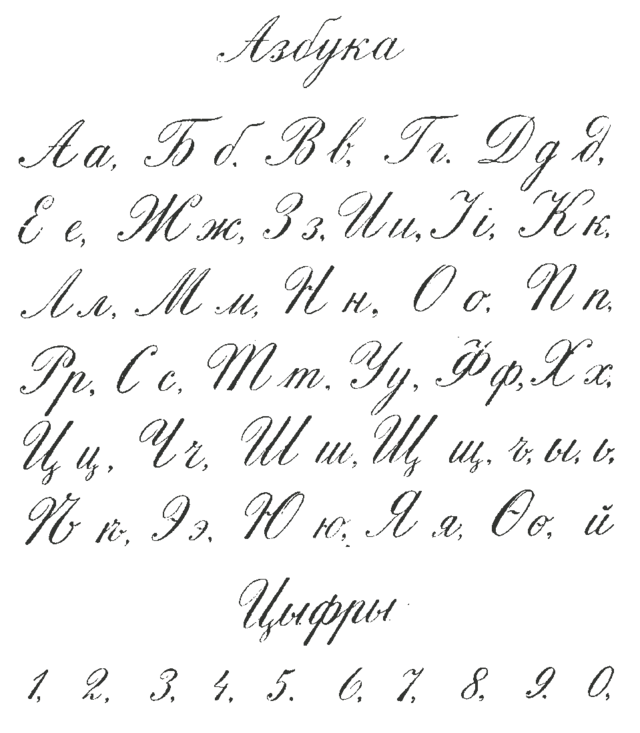
Рукописные шрифты особенности и происхождение гарнитур
Рукописные шрифты принято делить на следующие подгруппы:
- Формальные
- Неформальные
- Каллиграфические.
Первый известный рукописный шрифт, или скоропись (во Франции называемая lettre courante (беглый почерк), а в Англии — secretary hand (почерк секретаря), возник как формальное письмо и был нарезан Робером Гранжоном в середине XVI века, но самые первые основанные на рукописном письме гарнитуры, называемые канчелляреска, создали в Италии еще в конце XV века. Из гарнитур канчеллярески ХХ века стоит упомянуть Zapf Chancery (Герман Цапф, 1979) и Poetica (Роберт Слимбах, 1992) — расширенную гарнитуру с большим набором альтернативных символов, орнаментов и росчерков.
Формальные рукописные шрифты произошли от письма XVII века, у большинства из них наклонные, округлые буквы с соединительными штрихами. К этой категории относится много гарнитур, от строго формальной Snell Roundhand (Мэтью Картер, 1966) до универсальной Ashley Script (Эшли Хэвинден, 1955).
Неформальные шрифты ближе к естественному рукописному письму ручкой или кистью. Обычно в них присутствуют соединительные штрихи. Гарнитуры этой категории очень варьируются по внешнему виду: от непринужденной Brush Script (Роберт И. Смит, 1942) до размашистой Pronto (Алехандро Пауль, 2009).
Каллиграфические гарнитуры произошли от каллиграфического письма, буквы у них не всегда соединены и обычно выглядят как написанные плоским пером. Внешне гарнитуры очень отличаются друг от друга, как, например, сдержанная Vivaldi (Фриц Петерс, 1990) и экспрессивная Riptide (Тимоти Дональдсон, 1996).
Характеристики
У всех рукописных шрифтов есть один общий признак: они кажутся написанными от руки, а не отлитыми, высеченными или изображенными механическим способом.
Помимо этого, они варьируются по стилю и характеристикам и бывают формальными и неформальными, вертикальными и наклонными; у них высокий контраст ширины штрихов, а буквы угловатые, с длинными верхними и нижними выносными элементами; они соединяются друг с другом штрихом или стоят по отдельности.
Применение
В основном рукописные шрифты выполняют декоративные функции, поскольку почти ни один из них не подходит для набора текстовым кеглем или сплошным текстом. Чаще всего они используются для заголовков или акциденций.
Образцы рукописных шрифтов:
- Bickham Script (Ричард Липтон, 1997)
- Byron (Пэт Хиксон, 1992)
- Cascade (Мэтью Картер, 1966)
- Choc (Роджер Экскоффон, 1955)
- Citadel (Monotype Design Studio, 2003)
- Coronet (Роберт Хантер Миддлтон, 1937)
- lsadora (Крис Холме, 1985)
- Monoline Script (Monotype Design Studio, 1933)
- Riptide (Тимоти Дональдсон, 1996)
- Snell Roundhand (Мэтью Картер, 1966)
- Vivaldi (Фриц Петерс, 1970)
- Zapf Chancery (Герман Цапф, 1979)
Шрифты для проектов, планов и карт 12
В эту группу включены: шрифт Каллиграфический, шрифт Пром-
стройпроект и Древний (наклонный).
Каллиграфическое письмо (прил. 37 и 38) относится к скорописным
шрифтам и может с успехом выполняться ученическими перьями, авто¬
ручкой с ’’мягким” пером или шариковой ручкой. Шрифт может найти
применение при оформлении титула, авантитула и шмуцтитула сельско¬
хозяйственных атласов, а также для оформления других вспомогатель¬
ных графических материалов.
Шрифт выполняется с наклоном вправо под углом примерно 60 • По
быстроте исполнения он экономичен, в написании красив и хорошо чи¬
тается.
Прописные и строчные буквы шрифта просты и состоят из двух ос¬
новных элементов: основного (контрастного) и соединительного (пря¬
мого или овального). В основу построения большинства строчных букв
положен овал. Прописные буквы имеют более сложный рисунок.
При выполнении письма ученическим пером или авторучкой шрифт
приобретает ярко выраженный контрастный характер, но при этом сле¬
дует соблюдать чередование тонких и нажимных элементов, которые в
местах закругления круто, изящно и плавно переходят к соединитель¬
ному тонкому штриху.
Строчные нормальные буквы имеют плотность примерно 1:2, а широ¬
кие ж, м, т, ф, ш, щ, ы, ю — 1:1.
Буквы б, в, д, р, у, ф, ц, щ имеют выносные подстрочные и надстроч¬
ные элементы.
Прописные буквы разделяются на узкие (при плотности 2:4) —А, Е, 3,
О, С, Ь, Э, нормальные (4:4) -Н, П, Р, X, Ц и широкие (5:4) -Ж, М, Т, Ш,
Щ, Ы. Поперечные элементы прописных букв 3, К, Е, Н, Ю пишут не¬
сколько выше геометрической середины буквы.
Толщина основного элемента всех букв одинакова и составляет вели¬
чину (1/7) Н.
Буквы в словах пишутся слитно, причем для большей выразительнос¬
Концевые элементы у прописных и строчных букв могут быть петле¬
образными, пламевидными, овально-спиральными и капельными.
Шрифт может являться контурной основой для выполнения худо¬
Прежде чем создавать проект на своей машине, вы можете отредактировать шрифт. Для каждого шрифта можно настроить полужирный, курсивный, полужирный курсив и обычный стиль. Это можно сделать на панели вверху.